如何组合字体
已发表: 2023-10-05组合字体可能听起来很容易做到。 但如果您不仔细选择字体,结果可能会看起来很不和谐。 这可能无法确定您的信息的基调或基调,或者传达错误的品牌个性。 学习如何组合字体就像了解最常见的字体类别以及如何将它们配对一样简单。 这是字体配对的终极指南。
4 种最受欢迎的字体类别
在组合字体之前,有必要熟悉四种最著名的字体类别。 字体配对的目的是呈现出和谐且互补的版式设计。 字体配对设计必须融合在一起,传递预期的信息或图像。
以下是四种最常见的字体系列:
衬线字体
衬线字体是最古老的字体家族,其历史可以追溯到 15 世纪。 它的特点是每个字母顶部和底部的脚部延伸,称为衬线。 这些小线条或笔划与传统的粗或细字母相连。 此字体类别最适合想要传达对其行业的尊重、权威、传统或信任的经典品牌。
衬线字体示例:
- 英语字体格式一种
- 劳拉
- 梅里韦瑟
- 普莱费尔展示
- 巴斯克维尔
衬线字体徽标示例:
无衬线字体
无衬线字体出现于 19 世纪,这是衬线字体的对应字体。 这些字体没有每个字母附加的“衬线”或“脚”,这有助于其半圆形、干净的吸引力。 无衬线字体看起来简约,非常适合网站、博客和平面设计。 大多数现代品牌更喜欢这种字体系列,因为它看起来比其前身更加更新。
无衬线字体示例:
- 宋体
- 罗博托
- 打开无字体
- 来源 Sans Pro
- 黑体
无衬线字体徽标示例:
脚本字体
对于较短的标题,脚本字体是最佳选择。 这种类型类似于手写风格,有时会被误认为是装饰字体。 两者之间的细微差别在于脚本字体更加平衡和流畅。 脚本字体看起来女性化、艺术化、优雅。 这些字体深受那些想要令人难忘和脱颖而出的品牌的欢迎。 脚本字体也非常适合婚礼请柬和贺卡。
脚本字体示例:
- 满足
- 太平洋
- 诱惑
- 露西达脚本
- 舞蹈脚本
脚本字体徽标示例:
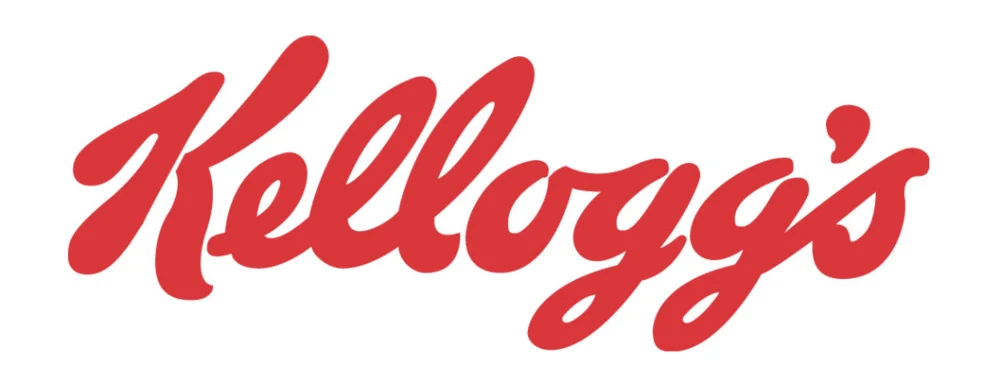
装饰字体
另一个独特而时尚的字体系列是装饰字体。 它们散发出一种看起来创新且富有创意的草书美感。 装饰字体与衬线字体和无衬线字体配对。 该字体系列展现出戏剧性和俏皮的风格化外观。 它还具有各种尺寸、形状、比例和形式。 品牌必须小剂量使用这种字体,因为独特且类似涂鸦的性质可能会压倒最初的预期信息。 或者不正确地使用这种字体可能不会有助于和谐或有凝聚力的设计。
装饰字体示例:
- 香肠
- 龙虾二
- 阿克斯韦尔
- 弗雷多卡一号
- 弗雷德丽卡
装饰字体标志示例:
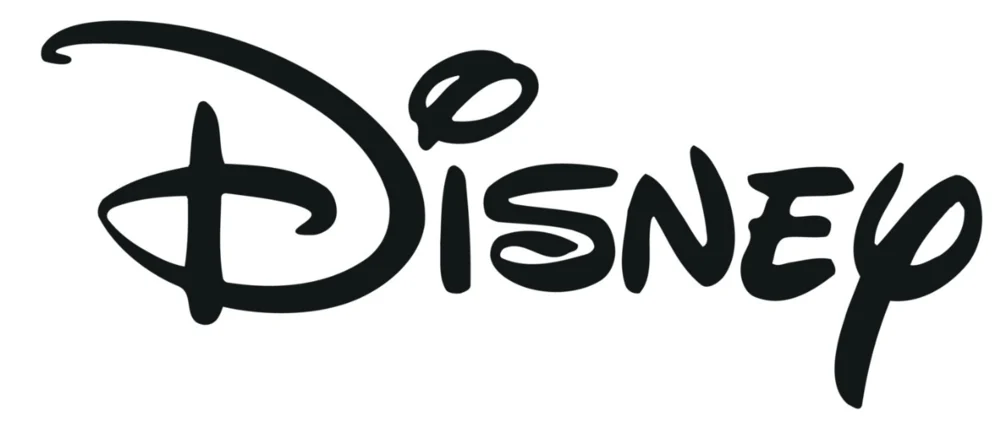
如何组合字体
现在您已经配备了最流行的字体系列,是时候学习如何组合字体了。 尝试多种字体是找到完美、有吸引力、脱颖而出的版式设计的关键。 话不多说,让我们直接深入了解字体配对技巧。
1. 仅限两种字体
限制字体配对最多使用两种字体并不是固定规则,但组合两种以上的字体可能会使您的设计变得复杂。 如果必须合并两种以上的字体,请选择互补的简单字体。
保持简单是迷人字体组合的关键。 如果您依赖徽标的排版,请尝试将其限制为仅两种字体。 拥有太多字体可能无法让每种字体都大放异彩。 每种字体都会争夺注意力,这使得创建完美构图的目标落空。
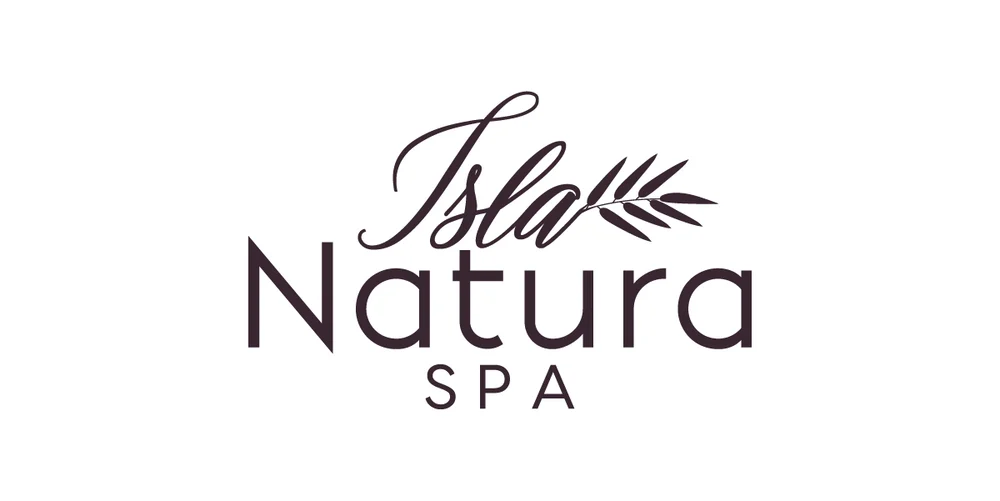
这是一个复杂的字体组合示例,展示了脚本和细无衬线字体。
2. 结合衬线和无衬线字体
结合衬线和无衬线字体可以帮助您实现平衡、可读性和优雅。 如果您不知道如何组合字体,这些都是安全的选择。 这是一个经典的字体配对技巧,几乎不可能搞砸。 衬线字体更清晰,可以快速地将眼睛从一个字母过渡到另一个字母,使这种字体易于阅读。
另一方面,衬线字体本质上更直接,更少分散注意力,更干净或更圆的边缘,非常适合更复杂的设计。 将两种字体结合起来,您可以创建引人注目且易于理解的精美排版组合。
借鉴 Prada 的标志。 该设计结合了衬线字体和无衬线字体,使字体更粗更细。 这种对比在多个元素之间创造了良好的平衡,文字“Milano”为眼睛提供了喘息的机会。
3. 从单一字体系列中选择
除非您是经验丰富的图形设计师,否则从单一字体系列中选择字体是最简单的途径。 因此,如有疑问,请坚持使用一种字体系列。 如果您仍在学习如何组合字体,选择字体系列并检查其类别下的样式可以更轻松地创建有凝聚力的布局。 不同字体系列下的每种字体都有不同的粗细和大小。
经验法则是不要选择两种相似的字体样式。 目标是建立多样性,使每个文本都流行。
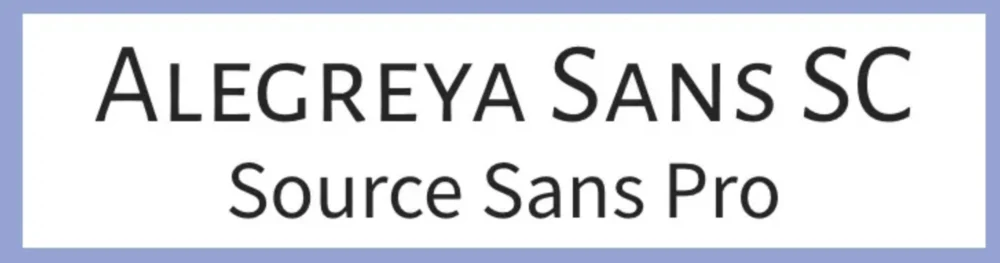
例如,该图像显示了无衬线系列下的两种不同的字体样式。 它结合了 Alegreya Sans SC 和 Source Sans Pro。 您可以通过使一个比另一个更粗或更显着来尝试权重。
4.选择对比鲜明的字体样式
经验法则表明将无衬线字体和衬线字体配对以获得差异。 但是,如果它们具有可区分的特征,您仍然可以从同一字体系列中选择字体样式。 如果配对的字体太相似,则无法建立层次结构,也无法区分其中一种。
另一方面,如果你将具有难以理解差异的字体配对,结果将是一场灾难。 确保您选择不同的字体,但仍然共享微妙的特征以实现凝聚力。 您可以尝试调整字体的字偶距、样式、大小和粗细。
要知道您是否选择了两种合适的字体,您可以并排放置两种不同的字体。 尝试从远处看比较并眯起眼睛。 如果字体看起来相同,则您已经实现了对比度和设计凝聚力。
以下是一些不同但具有相似功能的字体示例。 这些字体配对之所以有效,是因为它们在许多方面都有所不同,例如样式、粗细、大小和字距调整。
5.避免过多的对比
对比度对于保持眼睛的注意力至关重要。 然而,过多的对比度会使排版看起来像是一个错误。 如果一种字体与另一种字体太过不同,每种字体都会争夺注意力。 您的目标是使您的版式设计作为一个整体来吸引观众。 如果一种字体与其搭配的字体差异太大,则两种字体都会显得格格不入。
太大的视差会造成视觉不平衡,这与你想要达到的效果相反。 请记住,并非所有不同的字体都有效。 仍然具有一些共同品质的特定字体可能会实现视觉和谐。
这是一个糟糕的字体配对的例子。 两种脚本样式字体不匹配。 尽管重量、尺寸和字距都可以接受,但样式却并非天作之合。 “Bad”文字是一种看起来简单、现代、休闲的脚本字体。 另一方面,“字体配对”文字的曲线则更为复杂,散发出一种阴沉而正式的基调。
6.使用层次结构
如果您想建立信息的组织和顺序,层次结构至关重要。 根据重要性为每个文本赋予适当的大小和粗细将导致清晰的设计和简洁的结构。 相同大小字体的设计会显得单调。
例如,如果您创建公司徽标,则品牌名称应具有最重要的重量和大小。 业务类别或行业必须作为品牌名称的补充文本。 此外,如果您将字体组合用于海报设计,请始终使标题成为最大且最明显的文本。 副标题紧随标题之后,尺寸和重量稍小。 接下来是副本,其尺寸比其他所有内容都小。
这种层次结构确保观看者能够顺利地从一个文本细节过渡到下一个文本细节。 这也将告诉读者从最重要的细节到最不重要的细节。
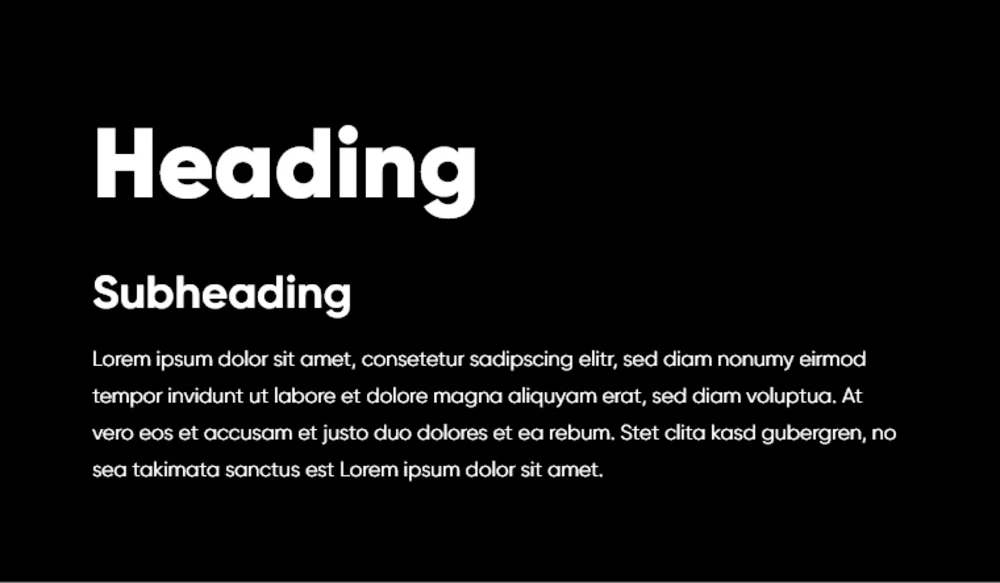
本文是良好结构如何提高可读性的最佳示例。
斐波那契数列
如果您不知道如何缩放文本,请尝试斐波那契数列方法。 通过添加前面的两个字体大小来确定层次结构的字体大小。
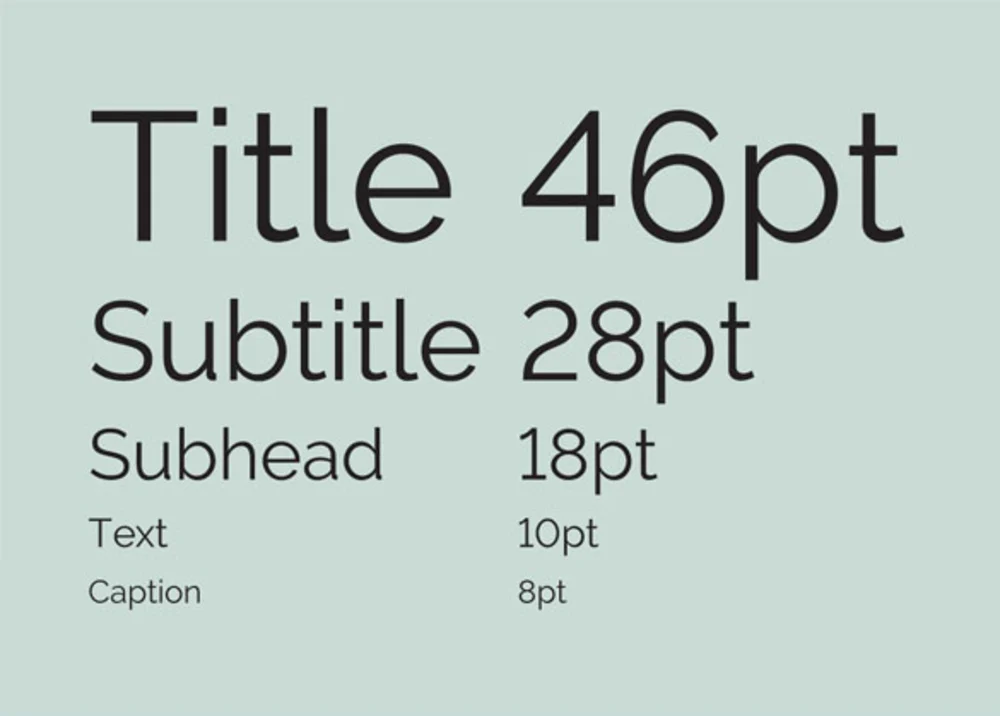
例如,如果您添加标题 (8) 和文本 (18),则总计 18,这应该是您的副标题字体大小。 假设您添加副标题 (18) 和副标题 (28),总计为 46,这应该是标题大小。
7.传达预期目的和情绪
与颜色一样,字体也依赖心理学来影响读者的决定。 无论是将字体用于宣传材料还是个人项目,每种字体都有自己的个性。 选择符合您的预期目的、信息或心情的字体。
例如,儿童材料应倾向于装饰性字体。 同时,正式文档必须包含简单衬线或无衬线字体。 字体会唤起目标受众的特定情感,因此在选择一种能够触动心弦的字体时要小心。
以下是有关如何根据您想要传达的信息和心情组合字体的快速指南:
力量与力量
如果你想传达力量和力量,请使用粗体、粗体的字体。 这些字体适用于金融或教育机构等更传统的公司。 大多数这些字体也用于促销材料或徽标的标题。 他们表现出稳定、值得信赖、权威和自信。
- 贝巴斯·纽
- 影响
由于LinkedIn是一个面向商业的平台,粗体、粗重的无衬线字体散发着专业的气息,符合社交网络的概念。
有趣和好玩
如果您的品牌更倾向于休闲和俏皮的一面,请尝试装饰或显示字体。 这些字体风格是非正式的,展现出更异想天开的吸引力。 这些字体非常适合儿童品牌、艺术项目和休闲活动。 建议谨慎使用装饰字体,以防止出现混乱的结果。
- 龙虾
- 漫画字体
优雅奢华
高端品牌必须考虑使用细笔画的衬线或脚本字体。 书法字体也传达出优雅和奢华,但又不显得不受欢迎。 这些字体非常适合婚礼请柬和高端产品包装。
- 爱德华七世时期的文字
- 比克姆脚本
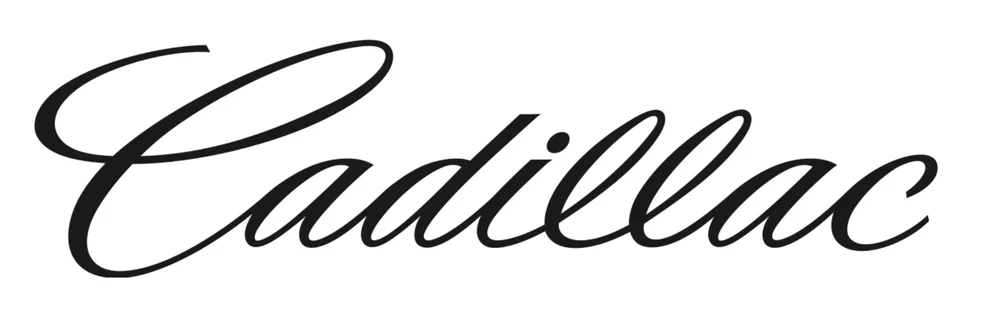
看看凯迪拉克的标志。 该品牌销售豪华汽车,这种字体恰恰传达了这一点。
友善和平易近人
如果您想与读者建立非正式的联系,请使用柔和的圆形字体。 这些风格营造出平易近人、友善的氛围,非常适合具有轻松休闲个性的品牌。 这些字体唤起温暖并与读者建立真正的联系。
- 努尼托
- 巴雷拉圆
8.限制字体数量
尽管将字体组合限制为两种或三种并不是一成不变的,但将其保持在这些数字内对于和谐的布局至关重要。 有些项目可能需要三种以上的组合,选择简单且不那么突兀的字体样式是最好的。
在学习如何组合字体时,请记住保持字体简单,最多使用三种字体组合。